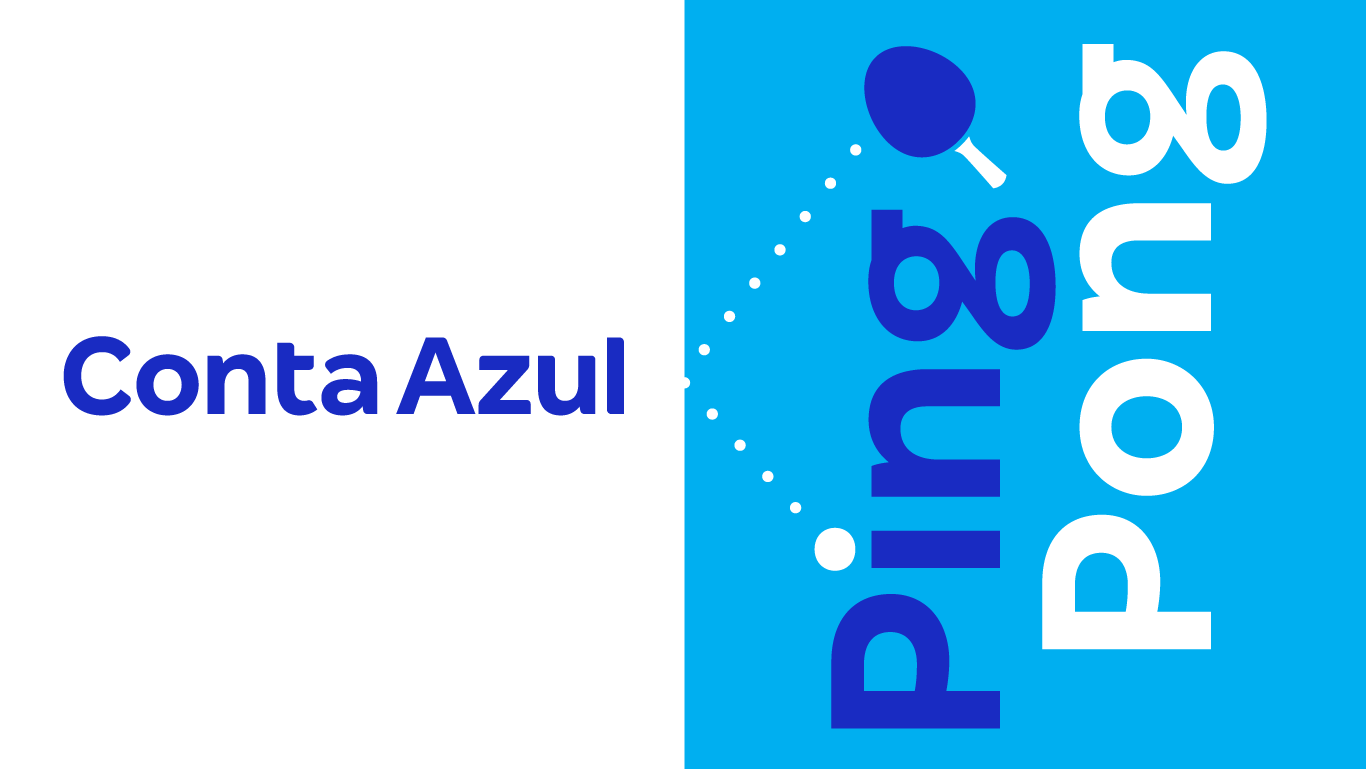
Ping Pong: a tipografia (e essência) da Conta Azul
Vinte anos depois, quem diria, tive o prazer de trabalhar para a Conta Azul, uma das empresas de tecnologia que mais cresce no Brasil, simplificando a gestão contábil já de 800 mil empresas, inclusive essa.
A convite do estúdio Firmorama, modificamos em conjunto a fonte Margem para criar uma versão exclusiva para o novo universo visual de Conta Azul.
A ênfase foi em aumentar o reconhecimento da marca em todos os pontos de contato, mantendo a leitura fácil e com visual proprietário.
Para isso, o desenho das letras ‘f’, ’t’ e ‘u’ foi simplificado, enquanto a letra ‘e’ se tornou mais suave, ligeiramente mais pessoal. Como ponto marcante, a letra ‘g’ ganhou uma construção distinta. São alterações pontuais, em letras-chave, que resultam em uma textura diferente da original, exclusiva da Conta Azul.
“Queríamos que a tipografia tivesse destaque no nosso universo visual. Com esse desafio, a Firmorama trouxe o Fábio para o projeto. Além da flexibilidade dele e do time, também tivemos um retorno bastante rápido em relação ao trabalho que precisava ser feito. Como resultado final, temos uma fonte bastante funcional, exclusiva e aderente a nossa estratégia de marca.” — Victor Zanini, Design Manager, Conta Azul
“Trabalhar com Fabio foi um processo bastante fluido e colaborativo, e também uma maneira de aprofundar os conhecimentos no desenvolvimento de fontes exclusivas, pois há uma grande generosidade em compartilhar. Experiência muito positiva que nós do Firmorama pretendemos repetir diversas vezes.” — Jackson Peixer, Diretor Criativo, Firmorama
O nome Ping Pong é uma homenagem às mesas de jogos que sempre estiveram presentes na Conta Azul. Segundo eles, um pequeno lembrete de que o caminho também pode ser divertido! E eu acrescentaria, que ele vai e volta.